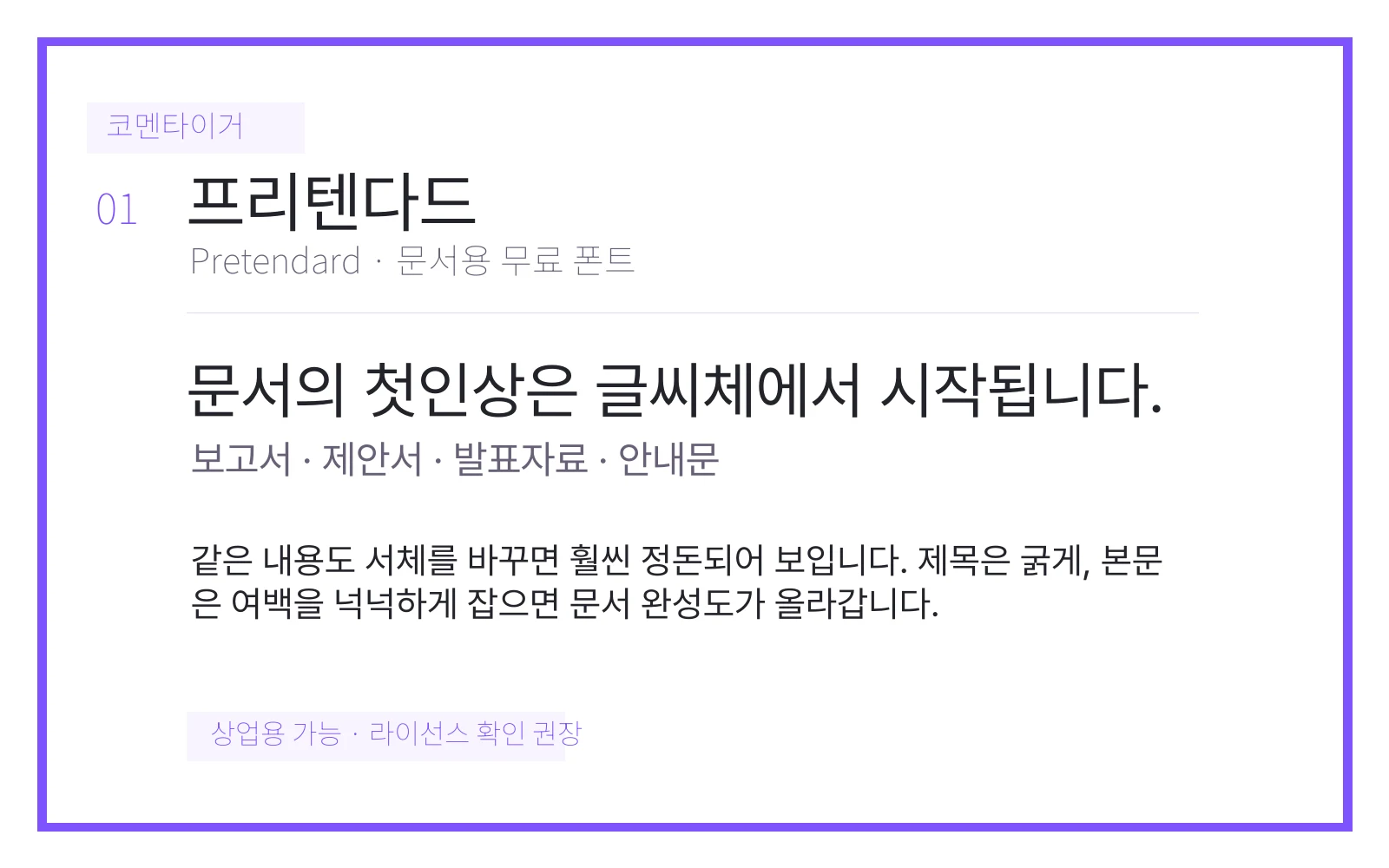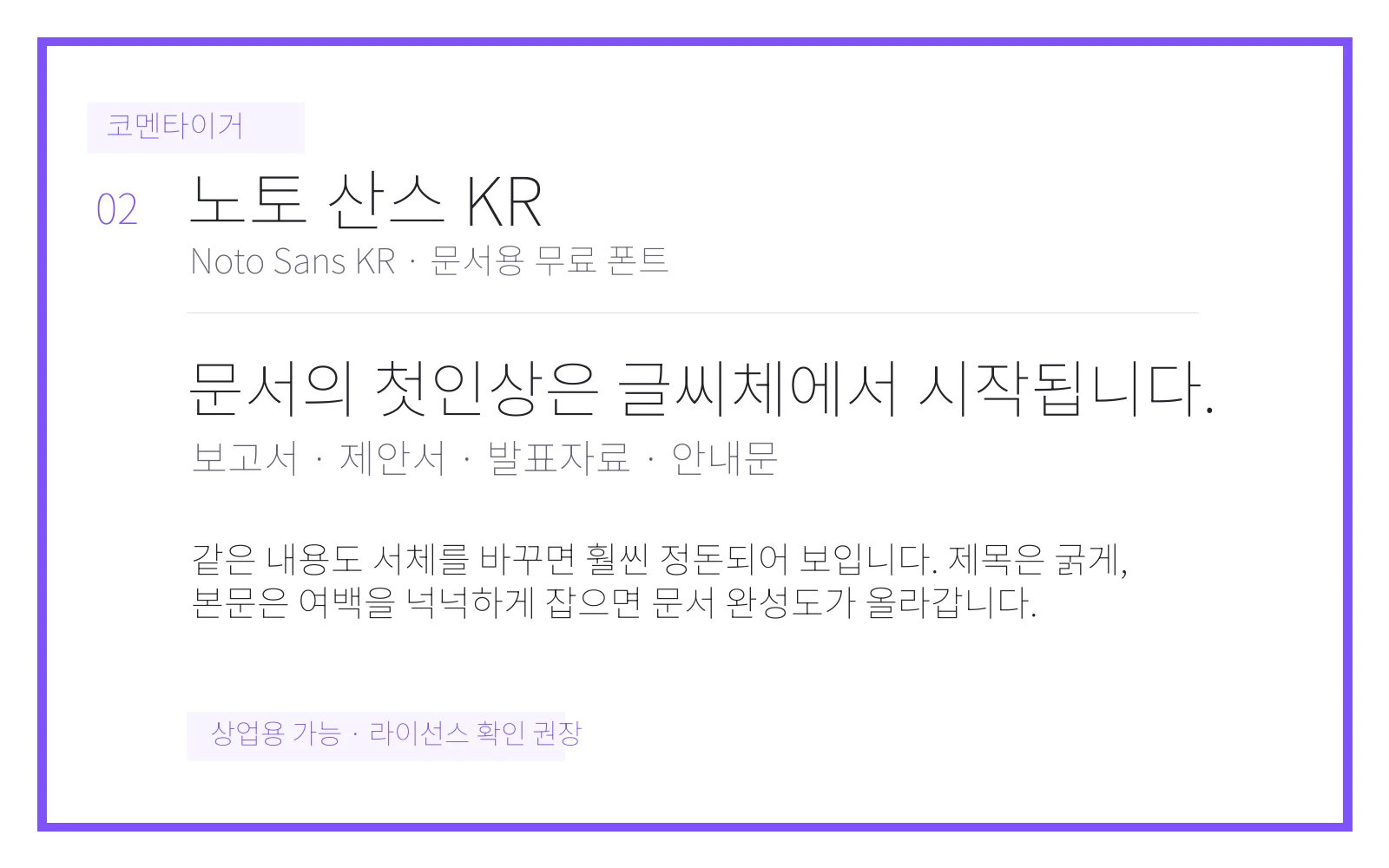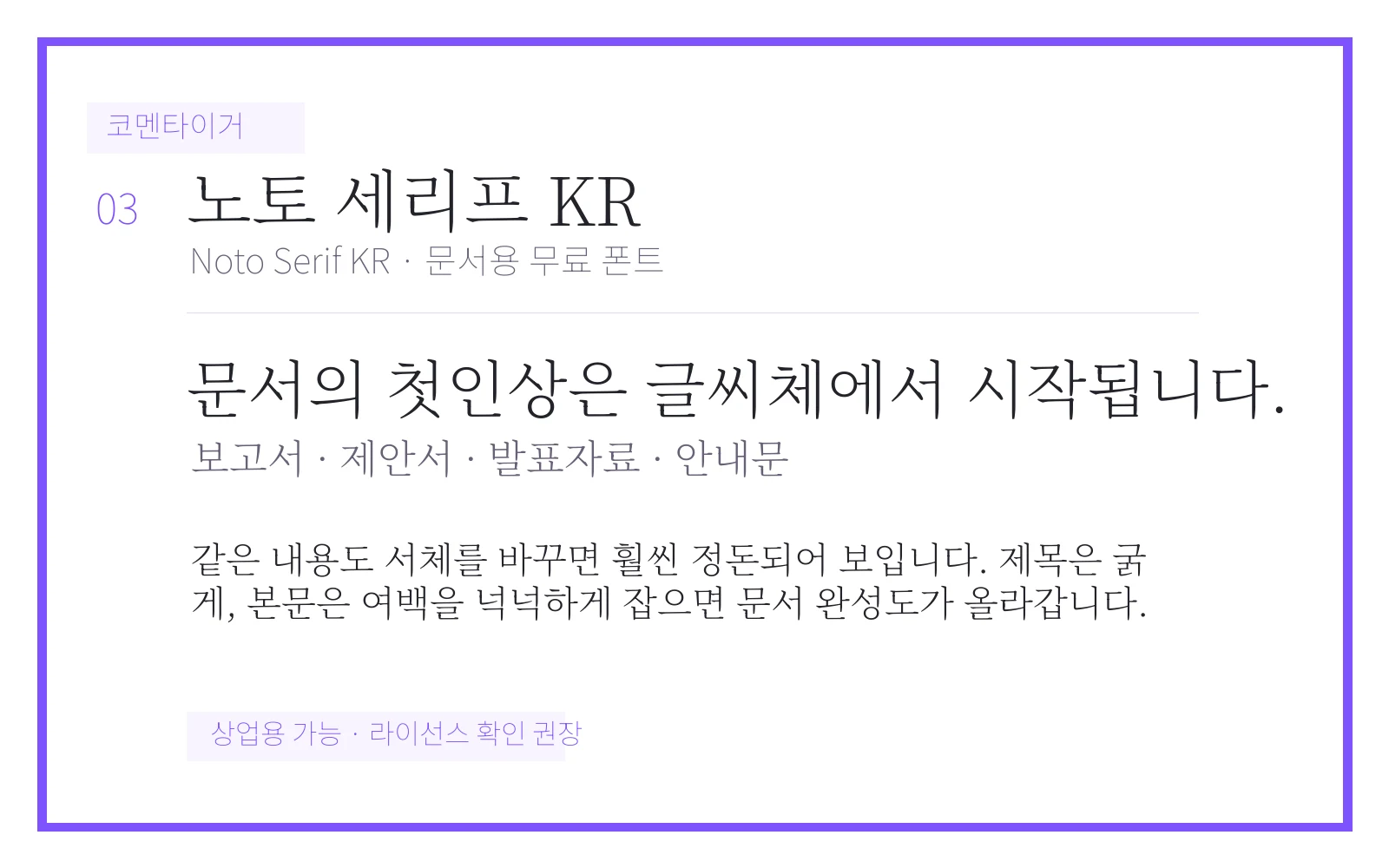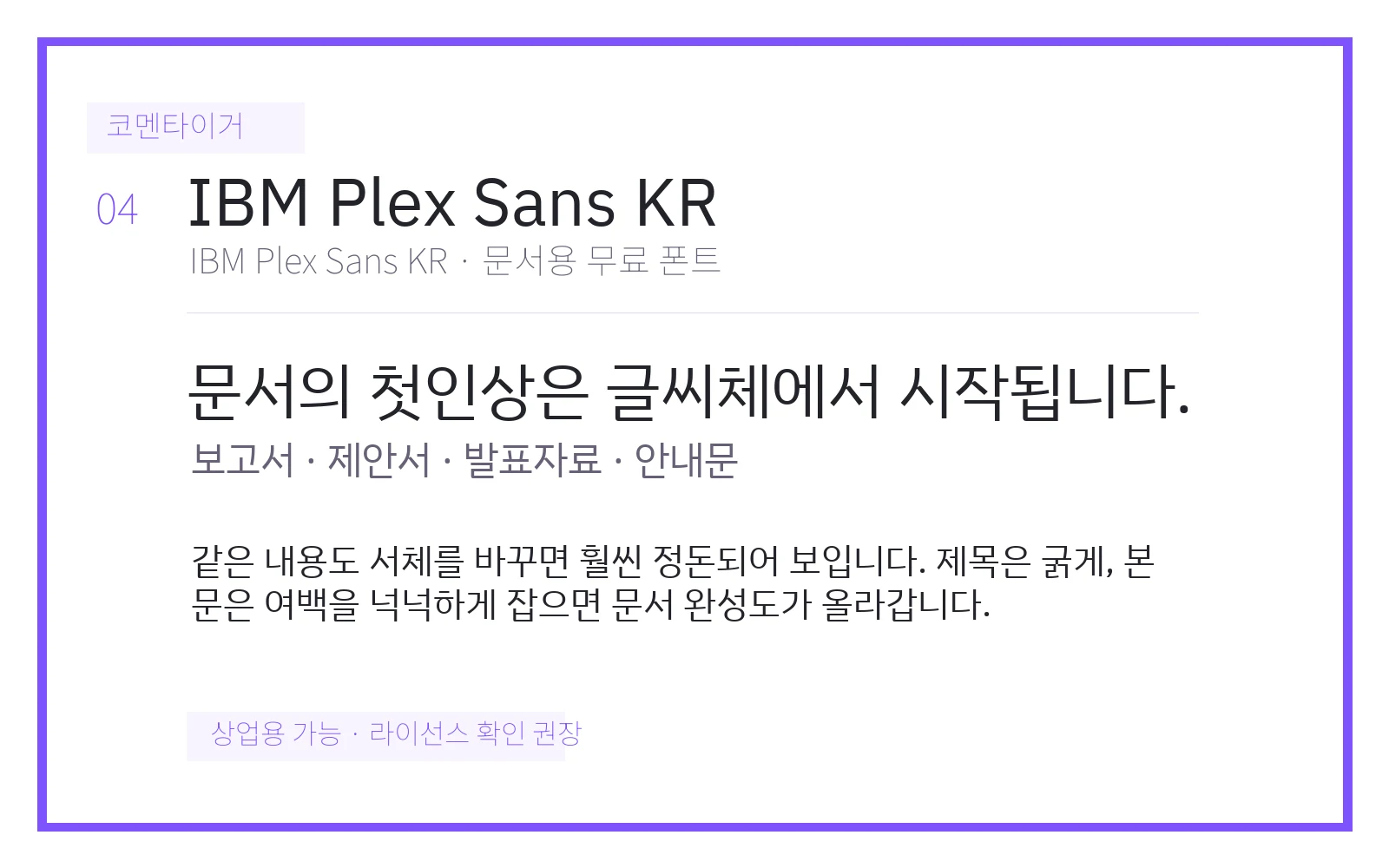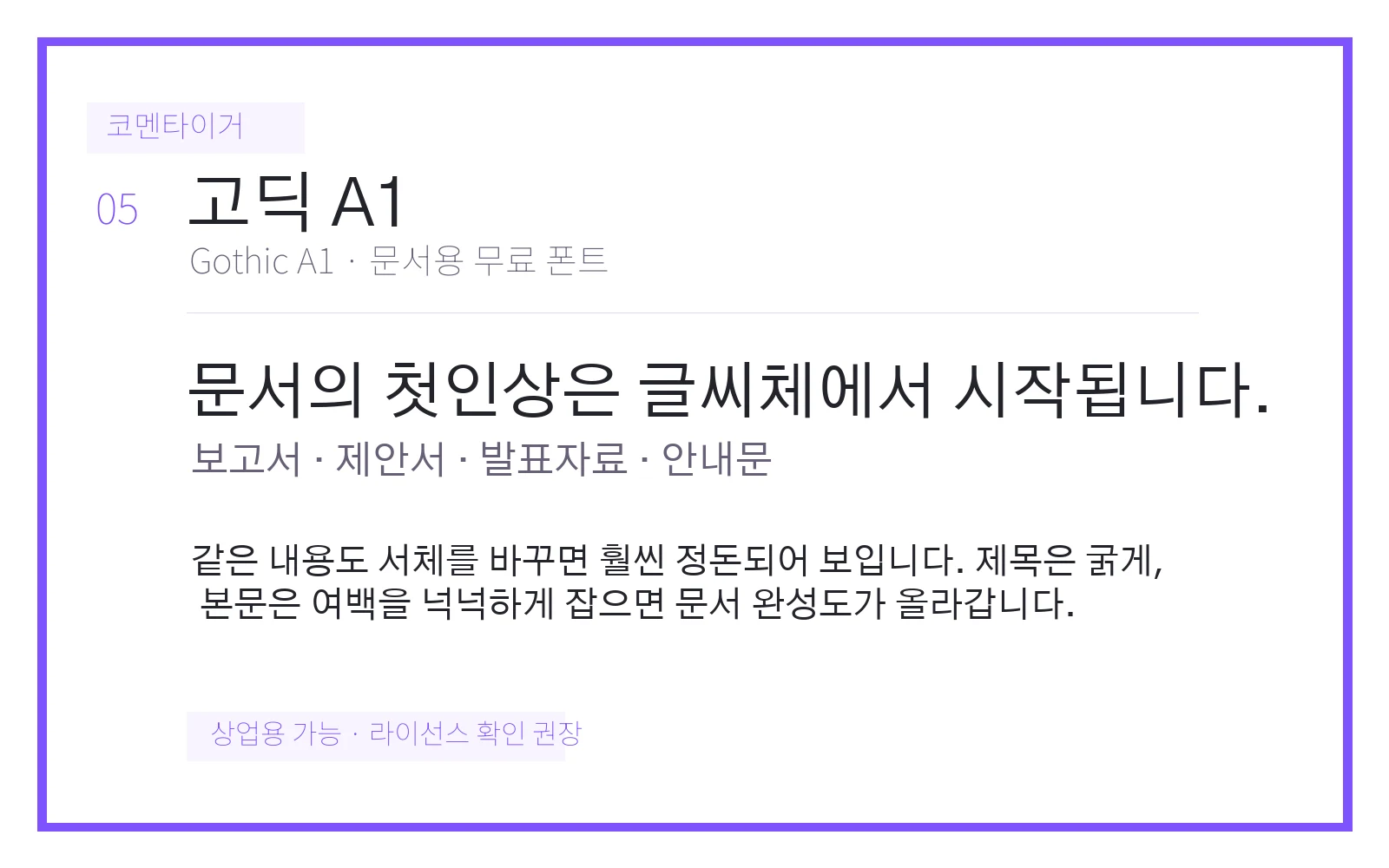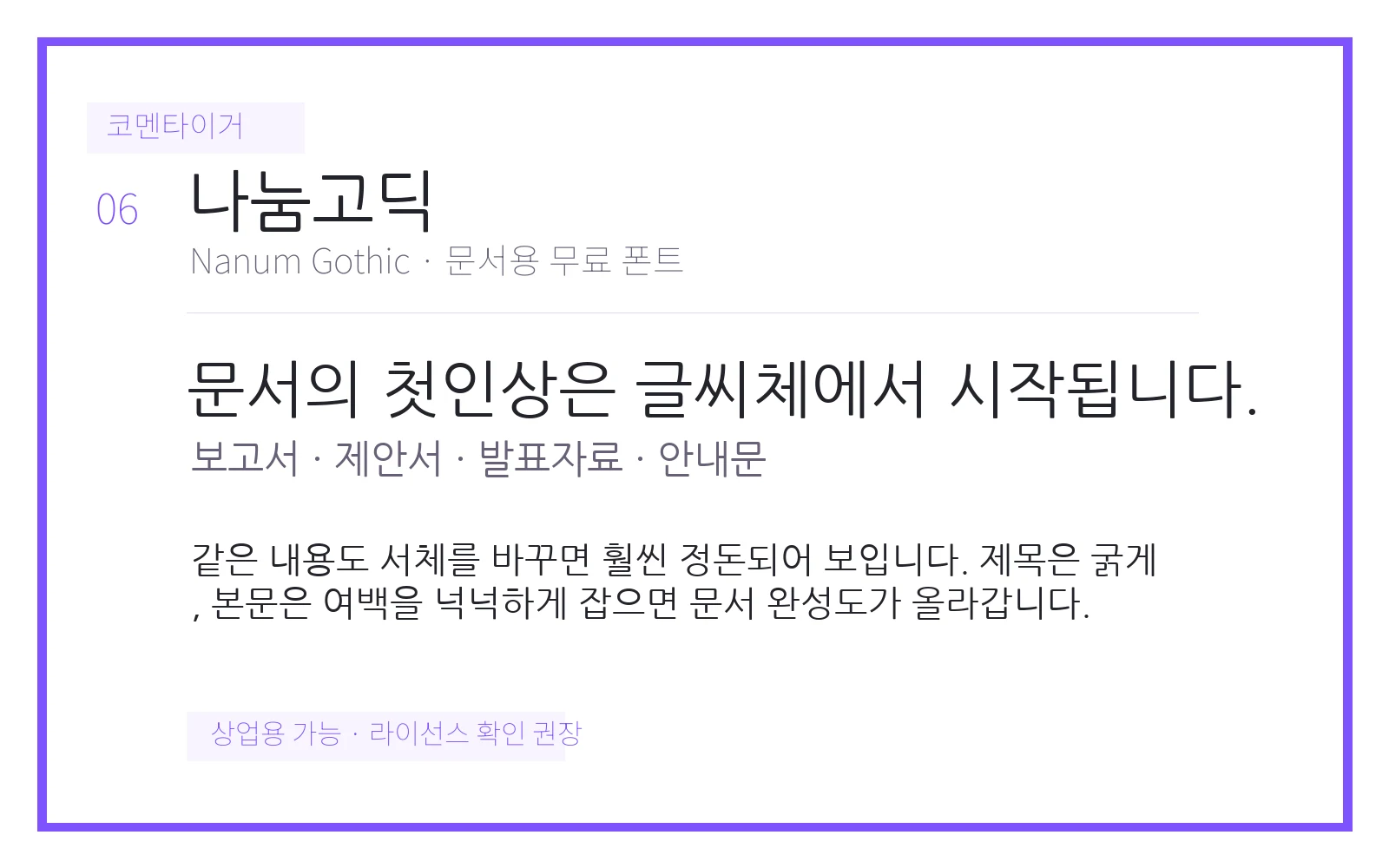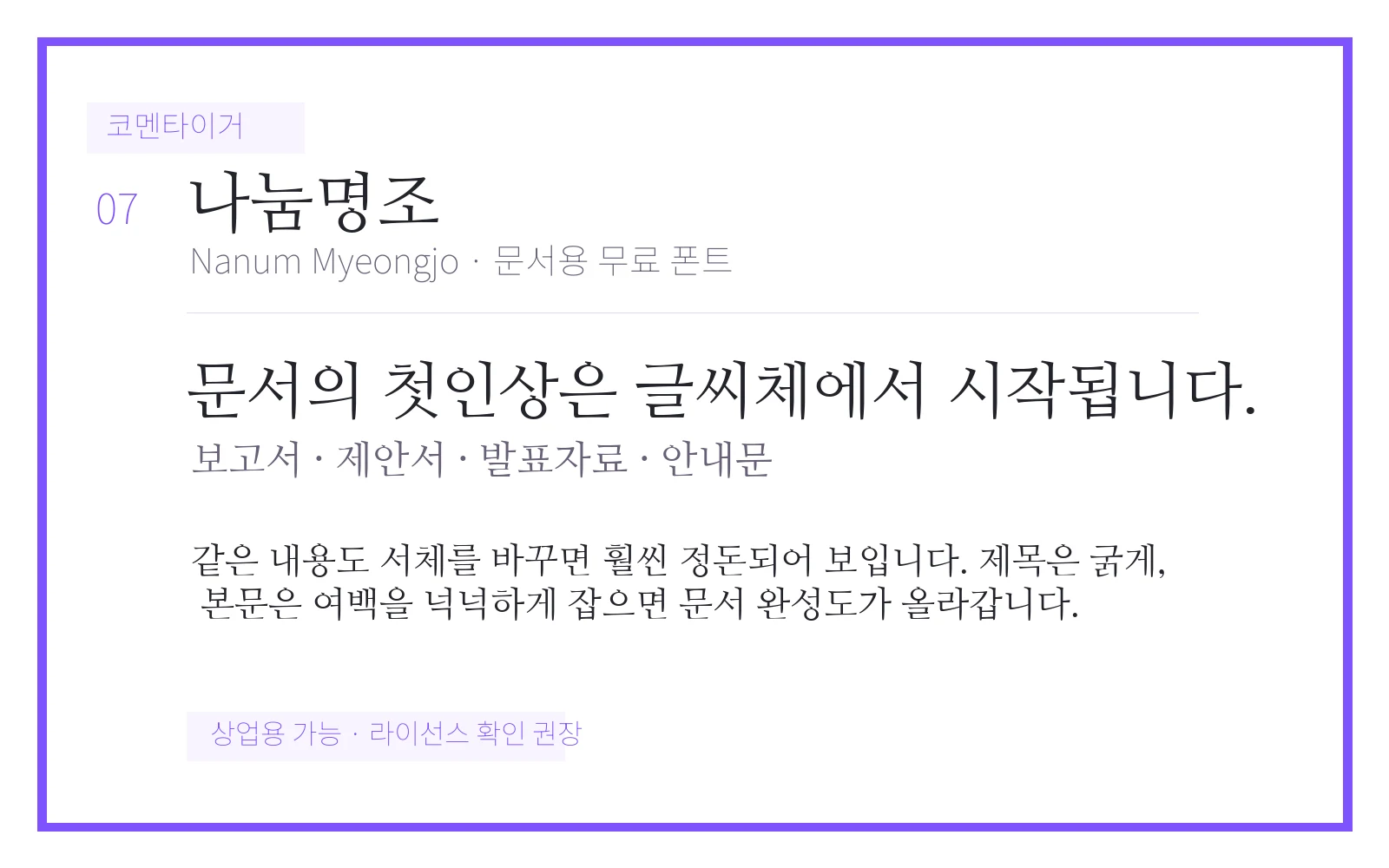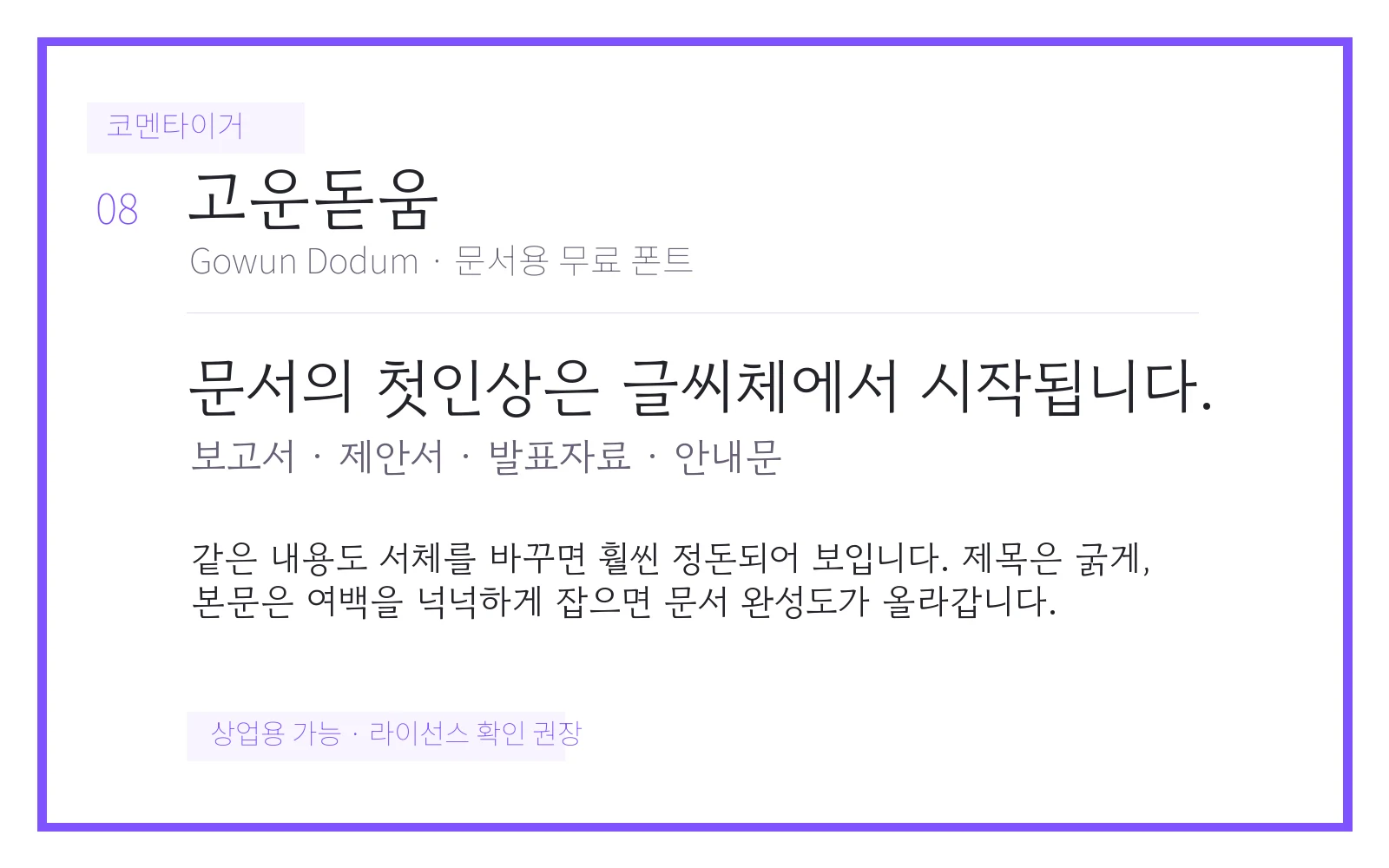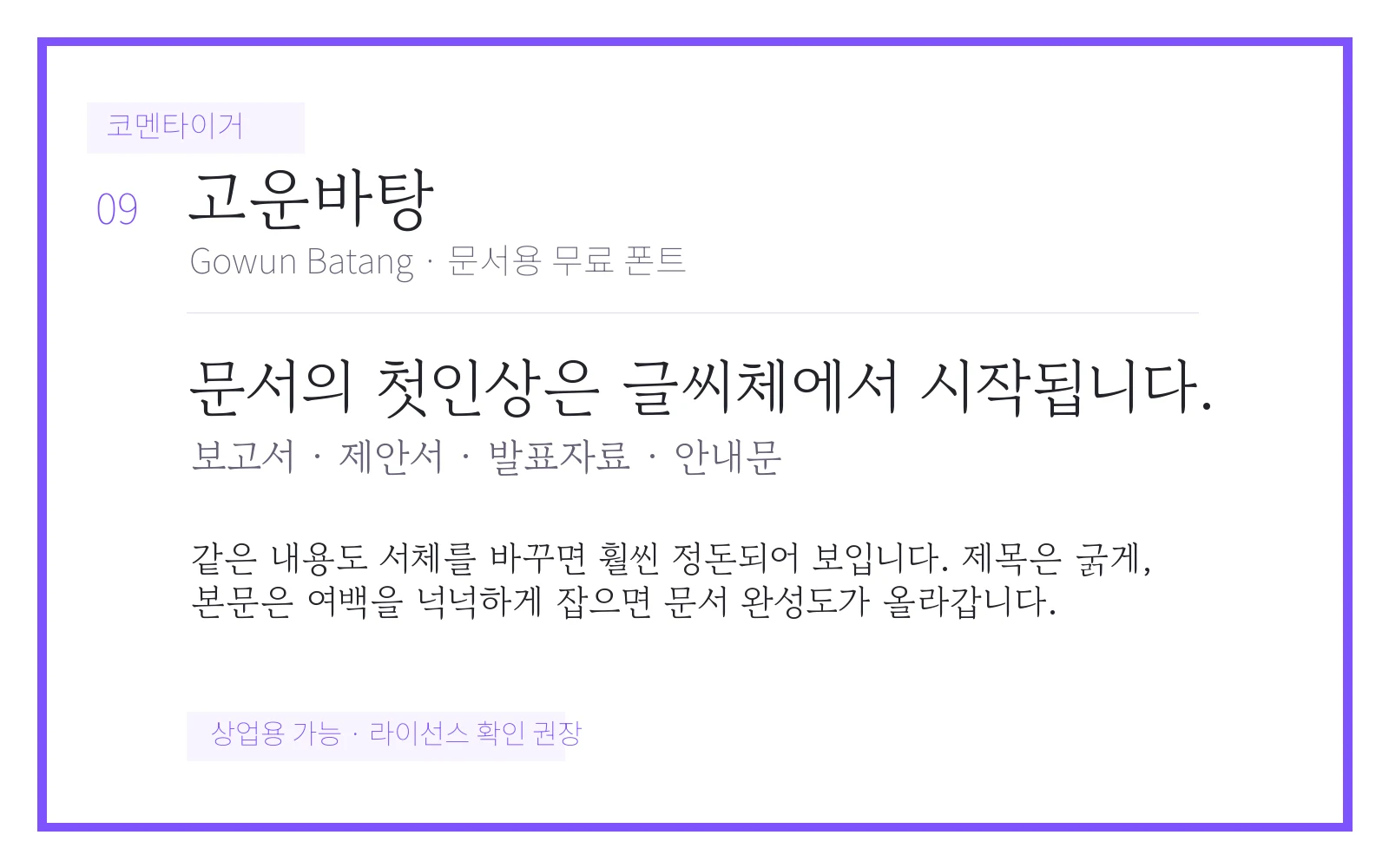
문서 퀄리티를 올려주는 무료 폰트 10개
문서가 어딘가 덜 정돈돼 보일 때는 내용보다 글씨체가 문제일 때가 있습니다. 아래는 보고서, 제안서, 발표자료, 안내문에 무난하게 쓰기 좋은 무료 폰트 10개입니다.
빠르게 고르는 기준
• 본문용이면 장식보다 가독성을 먼저 봅니다. 보고서·제안서에는 고딕 계열을 기본값으로 두는 편이 안전합니다.
• 제목용이면 굵기와 자간이 중요합니다. 한 문장만 크게 넣어도 모양이 무너지지 않는지를 봅니다.
1. 프리텐다드
• 추천 용도: 깔끔한 기본 고딕이라 보고서·제안서 본문에 무난합니다.
2. 노토 산스 KR
• 추천 용도: 가독성과 호환성이 좋아 가장 안전한 문서용 고딕입니다.
3. 노토 세리프 KR
• 추천 용도: 차분한 명조 계열이라 논문·리포트·긴 글에 잘 맞습니다.
4. IBM Plex Sans KR
• 추천 용도: 기술 문서나 회사 소개서에 어울리는 단정한 인상입니다.
5. 고딕 A1
• 추천 용도: 얇은 굵기부터 두꺼운 굵기까지 폭이 넓어 PPT에도 쓰기 좋습니다.
6. 나눔고딕
• 추천 용도: 익숙하고 부담 없는 인상이라 공지문·안내문에 편합니다.
7. 나눔명조
• 추천 용도: 문서에 격식을 주고 싶을 때 쓰기 좋은 명조체입니다.
8. 고운돋움
• 추천 용도: 딱딱하지 않은 돋움체라 교육자료·가벼운 설명서에 좋습니다.
9. 고운바탕
• 추천 용도: 부드러운 바탕체라 에세이형 문서나 소개문에 어울립니다.
10. 함렛
• 추천 용도: 제목과 본문을 함께 잡기 좋은 개성 있는 문서용 서체입니다.
짧게 고르는 기준
• 보고서·제안서: 프리텐다드, Noto Sans KR, IBM Plex Sans KR
• 논문·긴 글: Noto Serif KR, 나눔명조, 고운바탕
• 발표자료·안내문: Gothic A1, 나눔고딕, 고운돋움, 함렛처럼 굵기와 인상이 분명한 폰트를 먼저 비교해보면 좋습니다.
용도별 추천 정리
• 보고서·제안서 본문: 프리텐다드, 노토 산스 KR, IBM Plex Sans KR
• 차분한 인쇄물·책자: 노토 세리프 KR, 나눔명조, 고운바탕
• PPT 제목·섹션 타이틀: 함렛, 고운돋움, Gothic A1